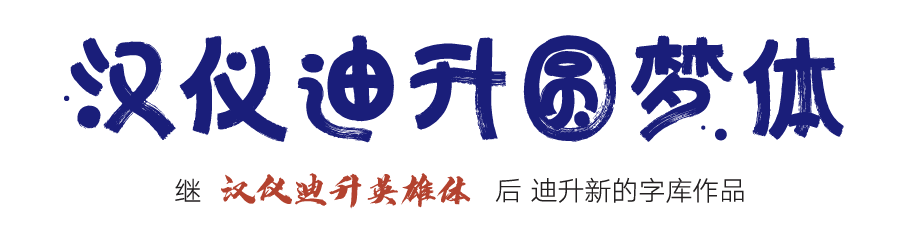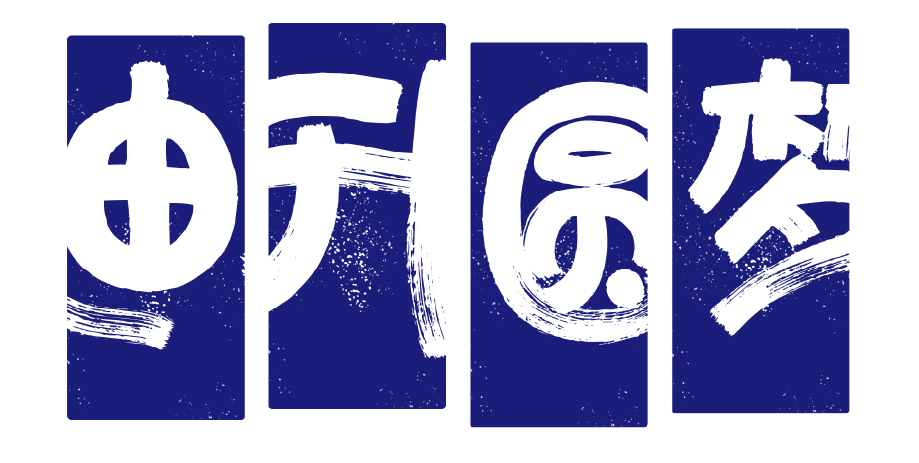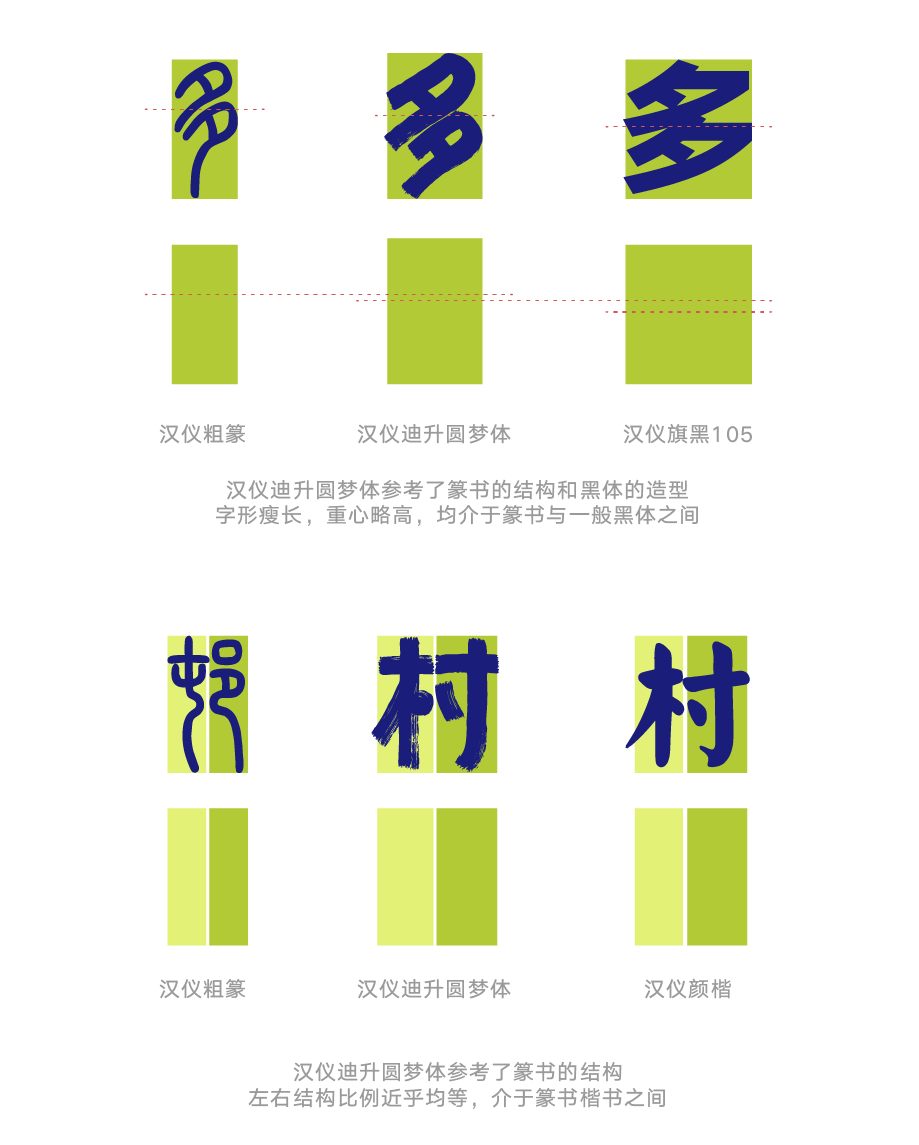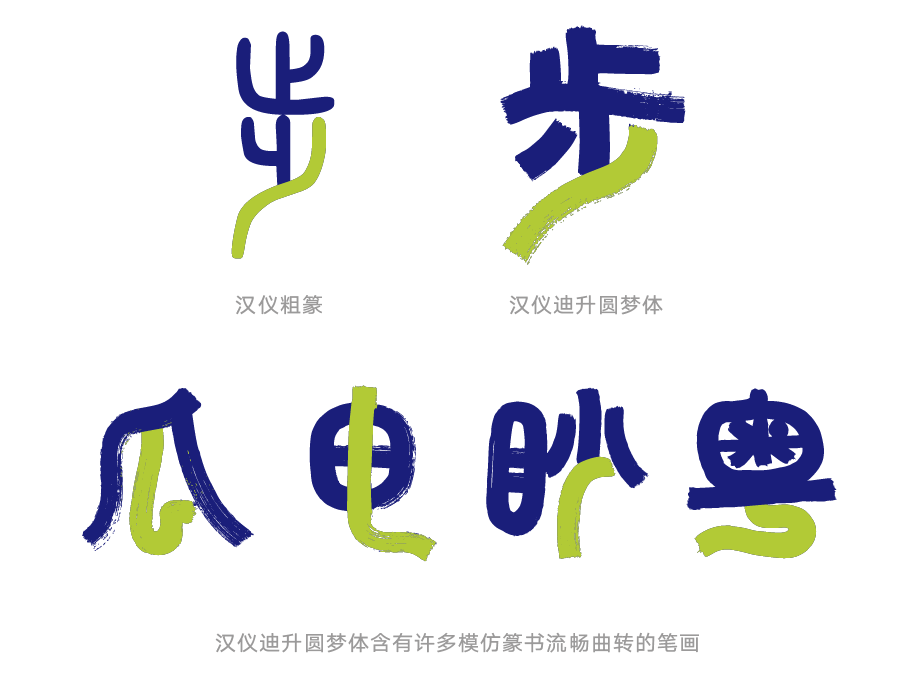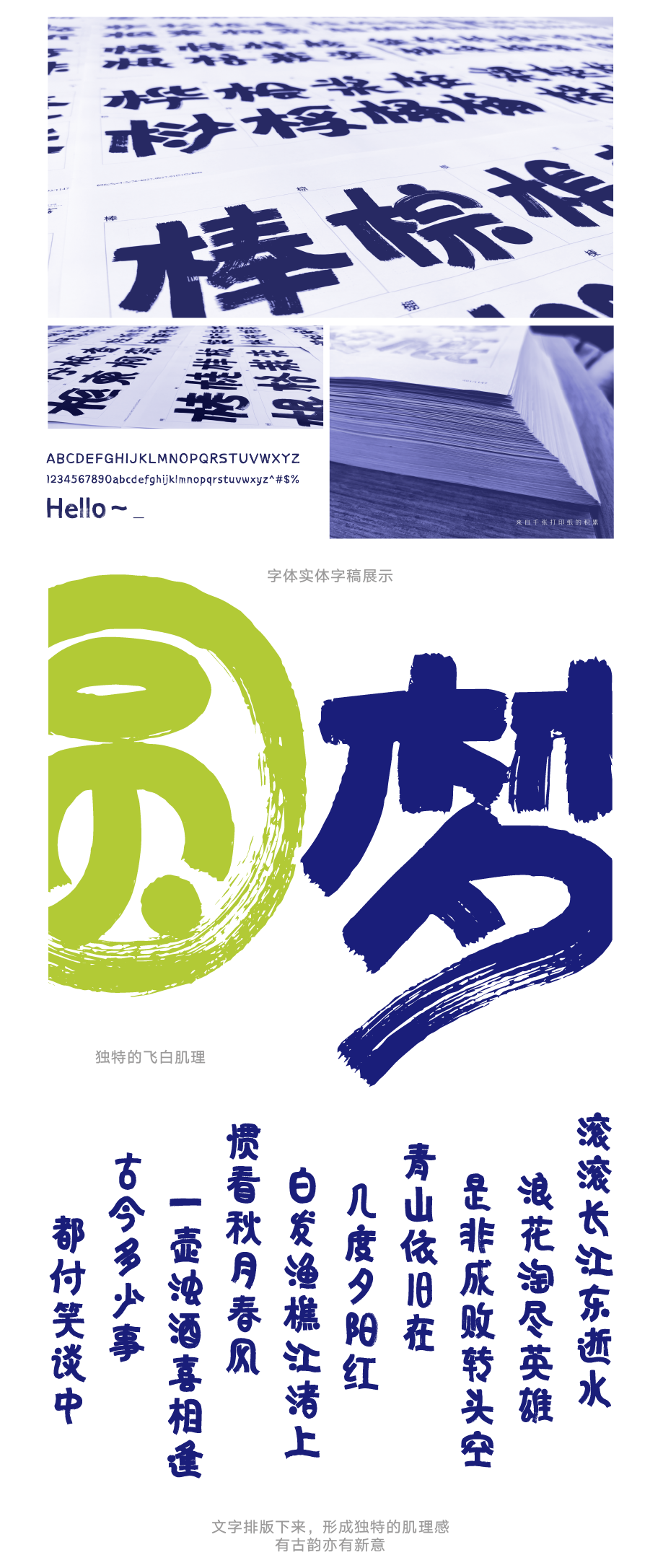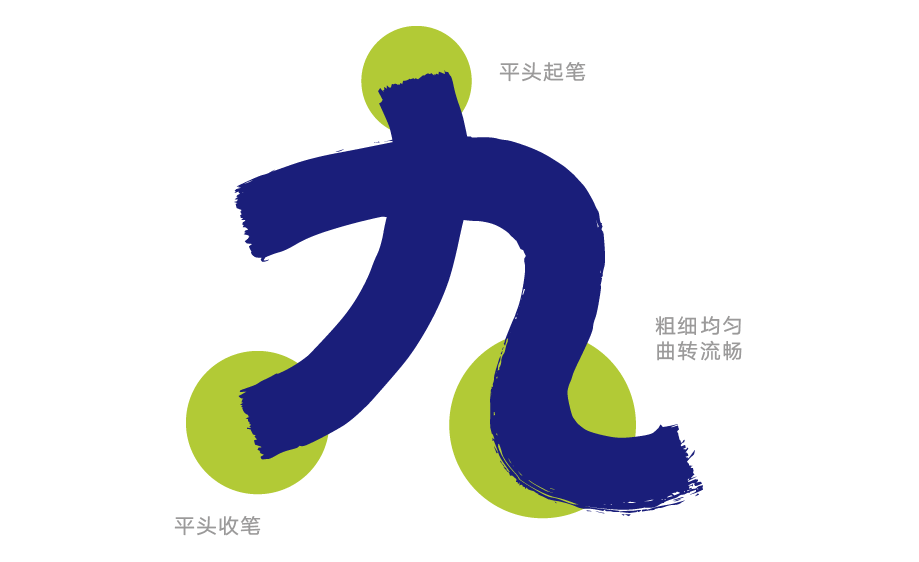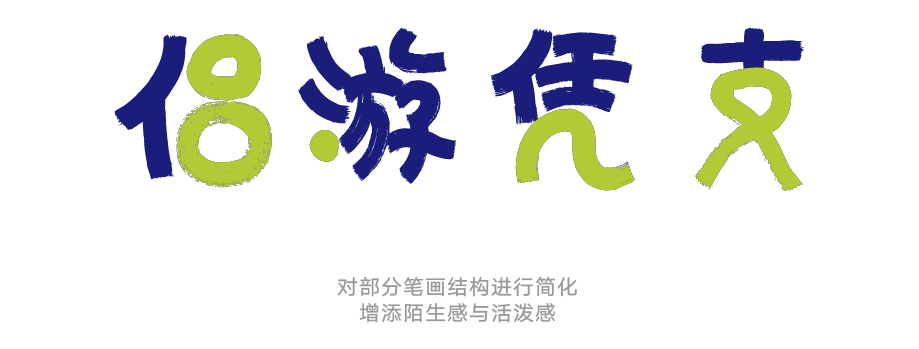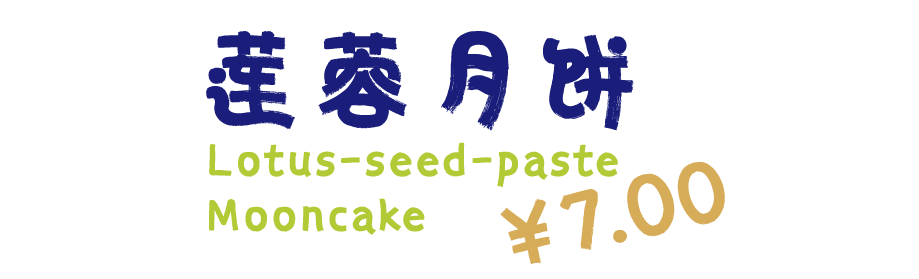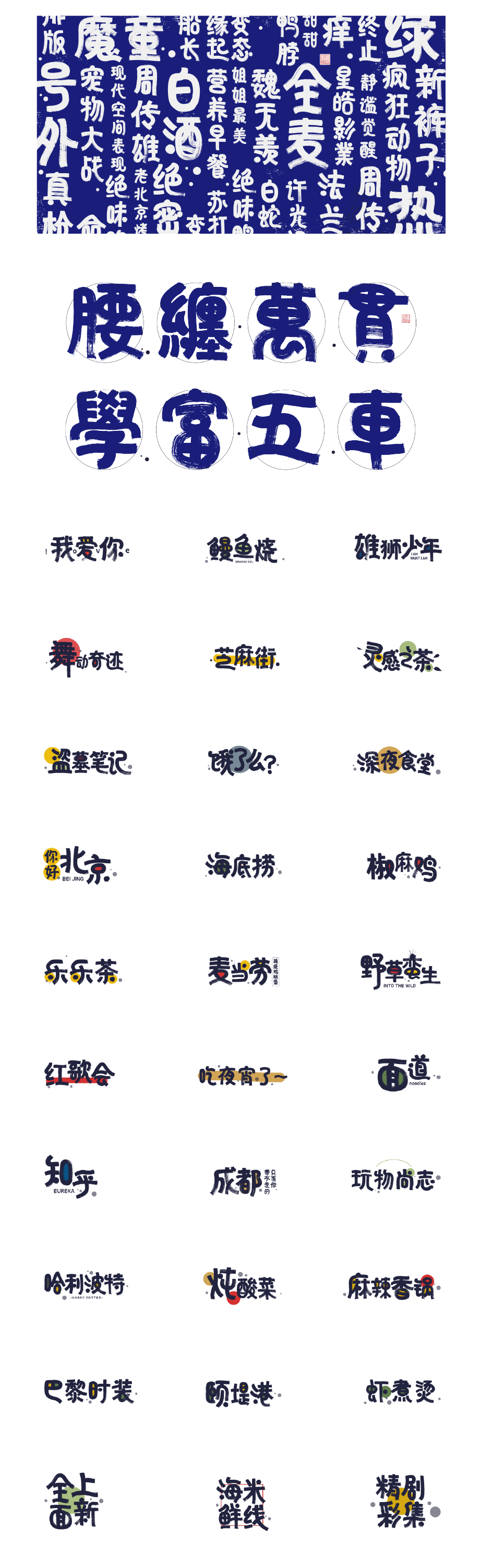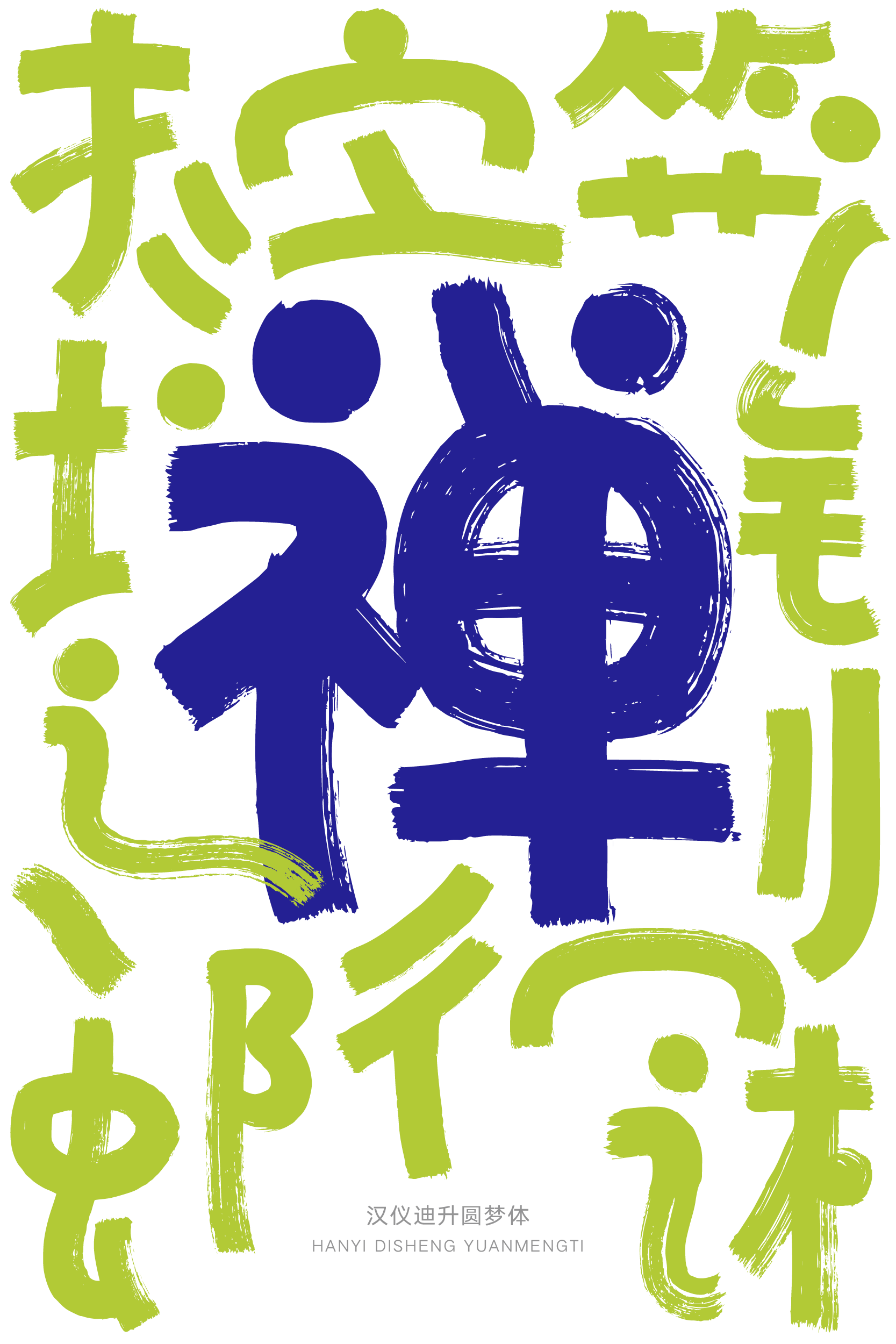
汉仪迪升圆梦体字体介绍,汉仪迪升圆梦体设计灵感
手书
传统 / 稳重 / 古韵 / 雄壮 / 大气
标志 / 广告 / 游戏 / 书籍排版 / 影视 / 包装
汉仪迪升圆梦体 | 字体介绍
汉仪迪升圆梦体由是青年艺术家、汉仪字库签约作者迪升创作的一款用水粉笔书写的手书字体。作者将飞白效果与活泼可爱的字形相结合,为字体增添了丰富的想象空间。适合作为标题字,应用在产品包装、动画海报、餐饮娱乐等各种需要表达大众、亲民、休闲、国潮等氛围的场景。
汉仪迪升圆梦体 | 吸纳篆书特征
作者在创作时,一定程度上参考了篆书的结构特征。字形重心高挑,左右结构均衡,笔画布局没有明显疏密变化。造型竖长但没有像传统篆书书法那样纤细修长,更易于设计师排版与应用。
在笔法方面,汉仪迪升圆梦体参考了篆书的笔画形态,绘制出大量流畅曲转的弧线笔画。与篆书的不同之处在于,该字体笔画弧度要更加圆润,同时笔画粗度也要比一般篆书要粗上许多,这使得该字体可应用的领域得到了拓展,方便设计师为多种场合创作。
汉仪迪升圆梦体 | 创新工具使用
该字体是用水粉笔在打印纸上一个个绘制出来的。作者在创作时充分运用了水粉笔的特性,绘制出这种带有独特飞白效果的字体。每个字形中都有枯笔润笔交相呼应,形成出一种独特的画面肌理。
作者在运笔时平出平入,绘制出这种水粉笔特有的起笔收笔方头形状。运笔时基本没有提、按动作,以行笔使转为主,所以字形笔画粗细均匀,曲转流畅。
汉仪迪升圆梦体 | 可爱字体造型
汉仪迪升圆梦体有着灵活多变的笔画造型,并且对部分笔画结构进行了简化处理,配合大量弧线笔画,使得字形整体看起来活泼可爱。运用在平面设计中,可以使得整个版面更具活力。
汉仪迪升圆梦体 | 中西文匹配
该字体西文部分也是由作者迪升亲手绘制的。西文部分中也含有大量飞白,中西文搭配使用,效果和谐统一。
汉仪迪升圆梦体 | 排版样张